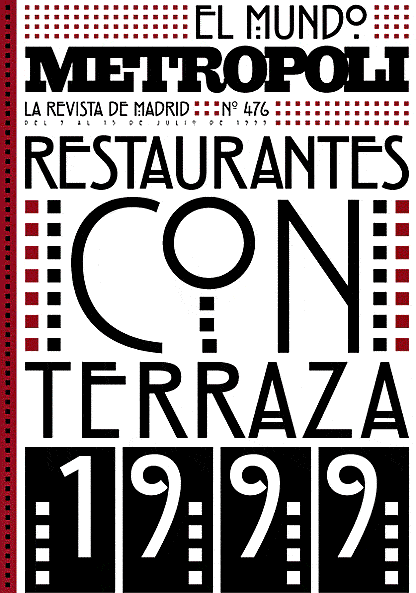
Un ITV de Rodrigo Sanchez, directeur artistique d’El Mundo
Le travail de Rodrigo Sanchez remarqué par le très célèbre Type Director Club de New York s’inscrit dans une tendance lettrage que nous avons connu dans les années 70 avec Herbert Lubalin mais aussi en France avec les Grapus. Une forme typographique que les situationistes de mai 68 ont pratiqué avec passion pour dénoncer la société de conso…ce qui fait que repris aujourd’hui dans un contexte contraire on peut bien entendu se demander si la forme attribue bien le même sens dans les deux époques. Mais on s’est déjà posé ces questions en analysant l’œuvre de Neville Brody qui de même avait récupéré le constructivisme des années 20 de la Russie Bolchévique pour… mettre en scène des magazines de Mode (Face, Arena, Actuel) pouvait effectivement passer pour une provocation intellectuelle extrême surtout en connaissant l’esprit caustique de Neville. Je vous laisse admirer ces posters de Sanchez sur le site de SpeakUp qui reste au demeurant un des meilleurs blogs professionnels que je connaisse. Ne saurait que vous inviter à en «prélever» le fil RSS.